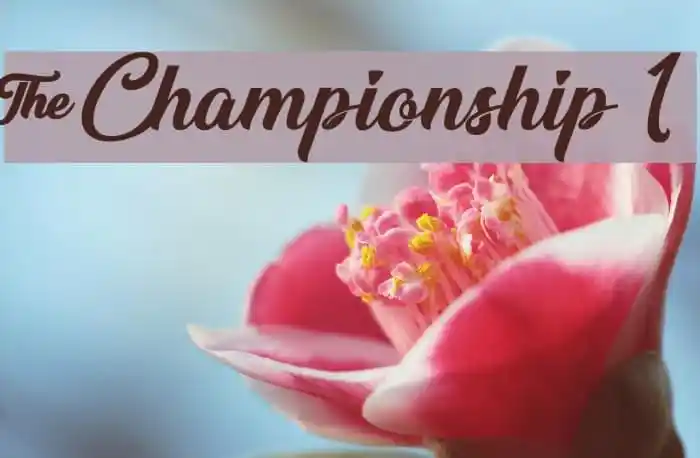
Championship Script Font – Download Grátis
Aqui está uma descrição em português do Brasil para a página de download da fonte “Championship Script Font”: Se você deseja usar nossa arte em projetos pessoais, este é um belo truque: é completamente gratuito. Mas se planeja incorporá-la no seu trabalho comercial, certifique-se de entrar em contato conosco antes. A fonte “Championship Script” foi criada pelo designer Hamilton e apresenta uma tipografia fluida e elegante que torna qualquer projeto mais sofisticado e atraente. Através da sua perfeita combinação de linhas suaves, detalhes profundos e harmonia, esta fonte é ideal para criar cartões postais, editoriais de revistas, design gráfico ou até mesmo publicidade. Seja você um designer ou um aficionado pela arte digital, a “Championship Script” proporciona uma ferramenta perfeita para se expressar em projetos pessoais e comerciais sem encargos adicionais. Com certeza, vale a pena experimentar esta fonte única que destaca seu trabalho. Não esqueça de entrar em contato conosco antes do uso comercial. Obrigado por visitar nossa fonte de arte digital.